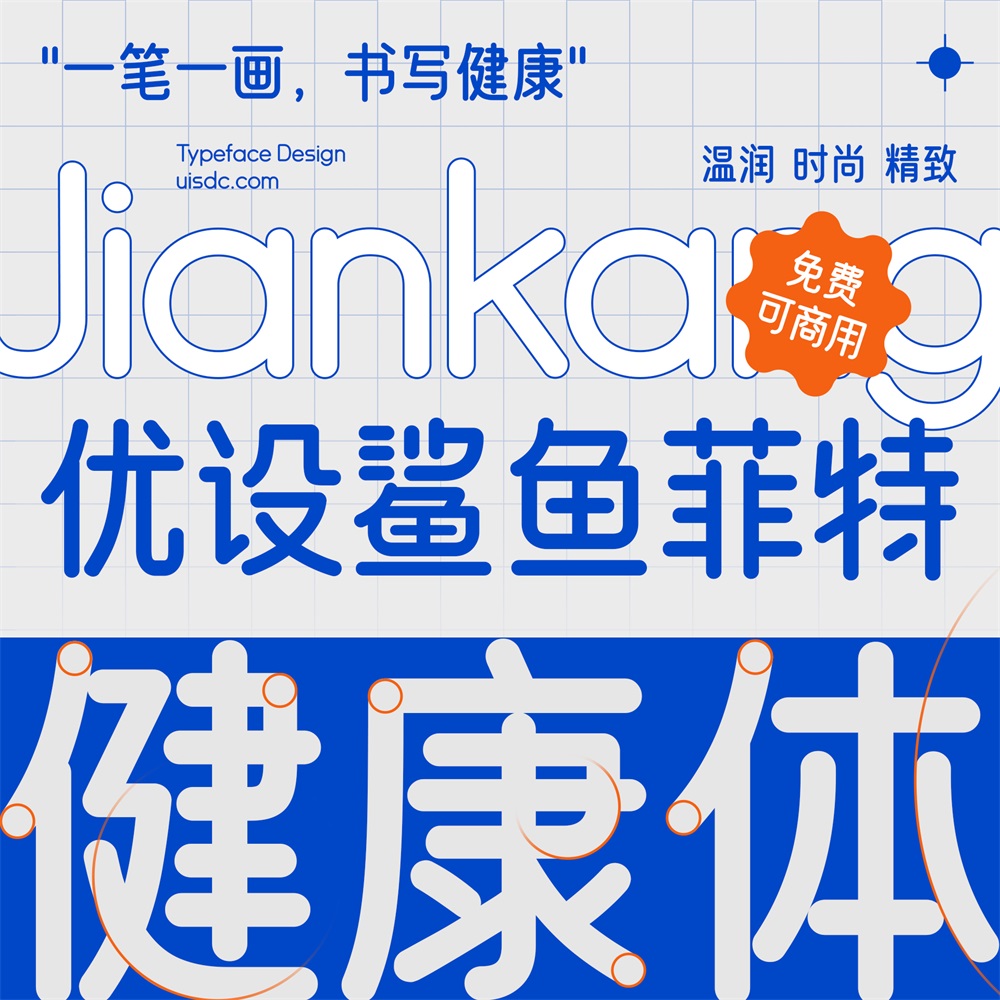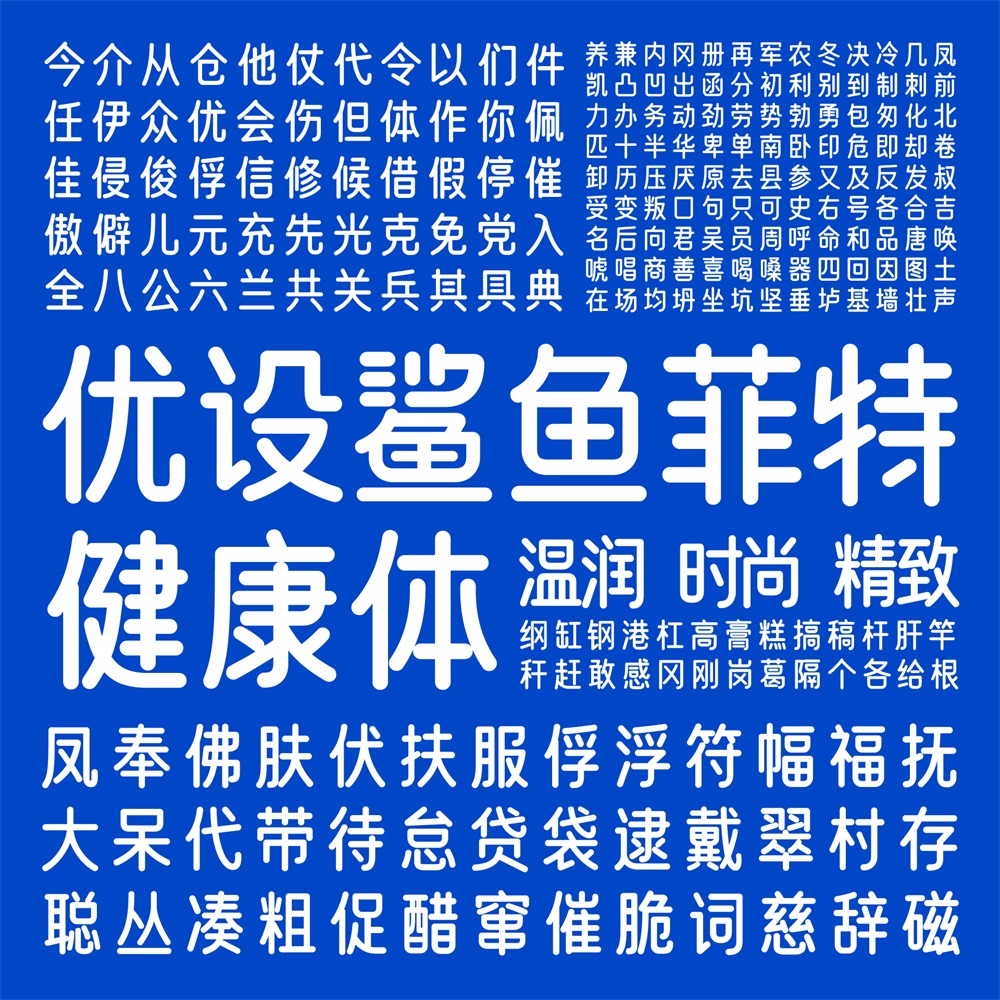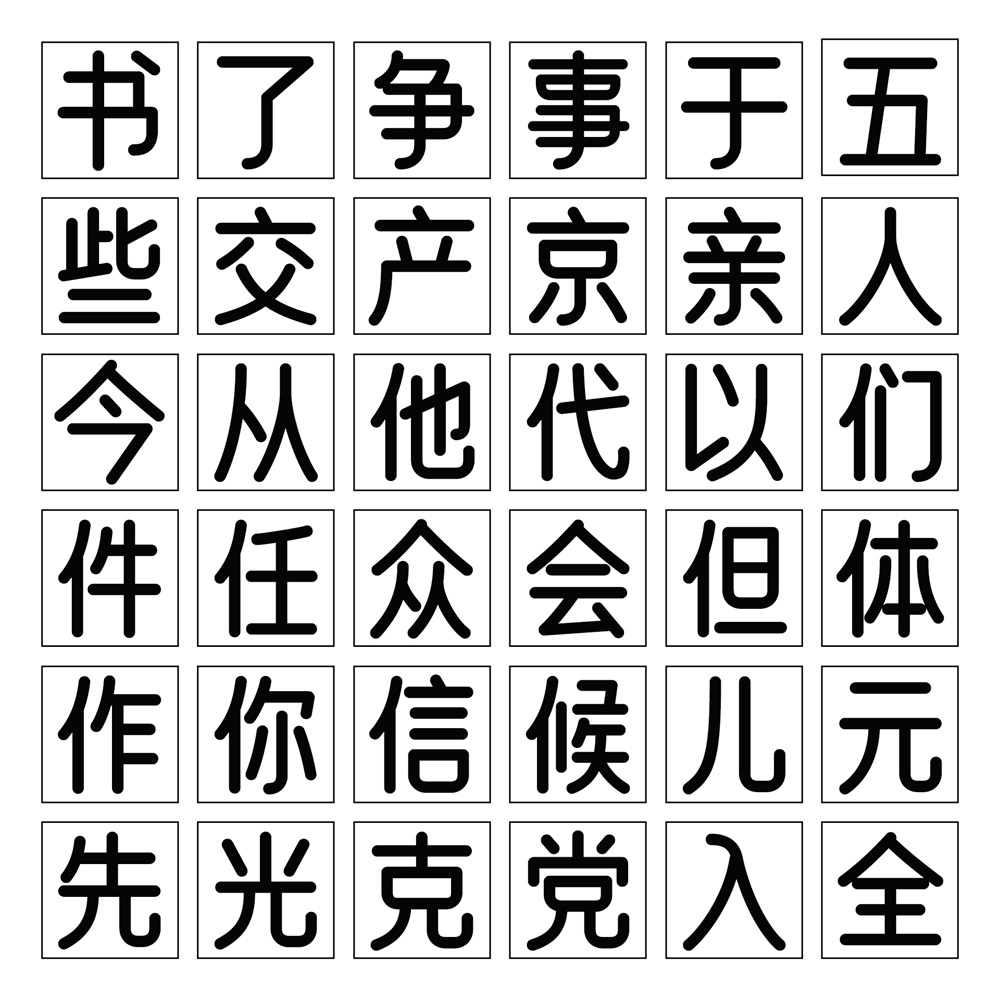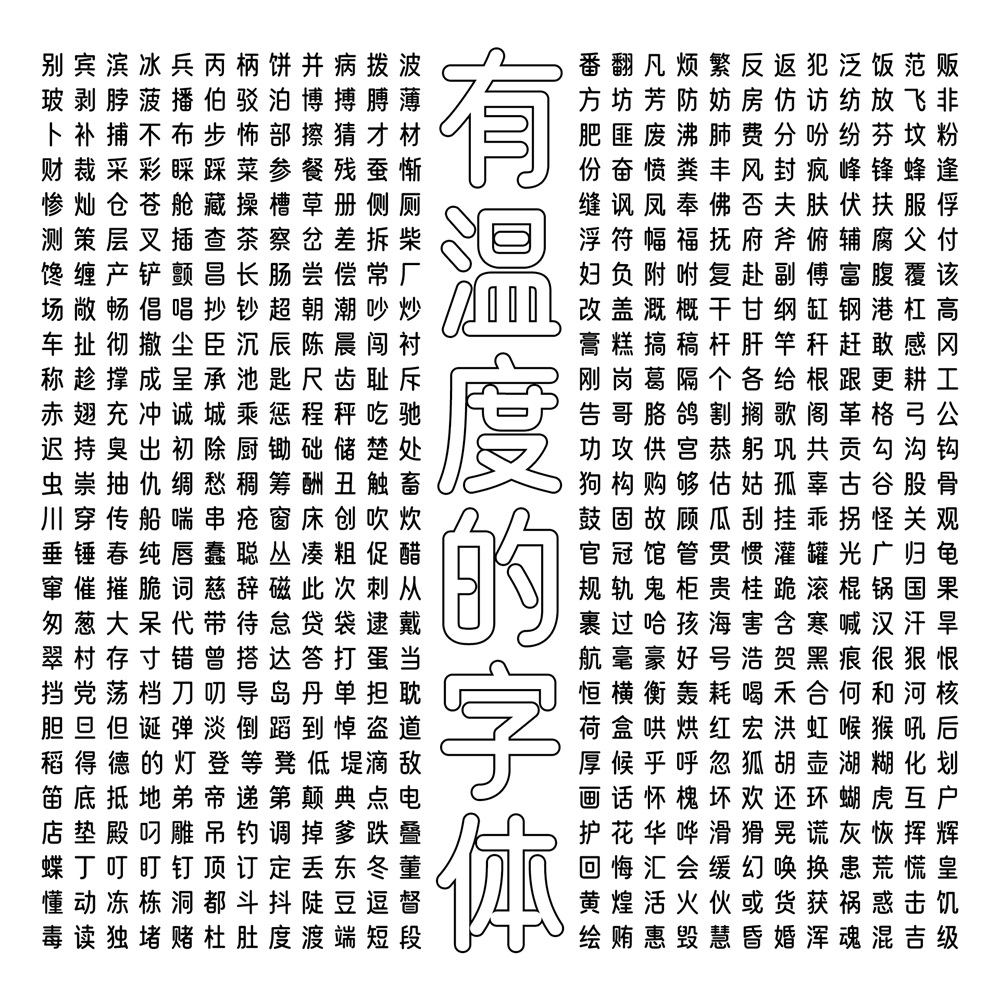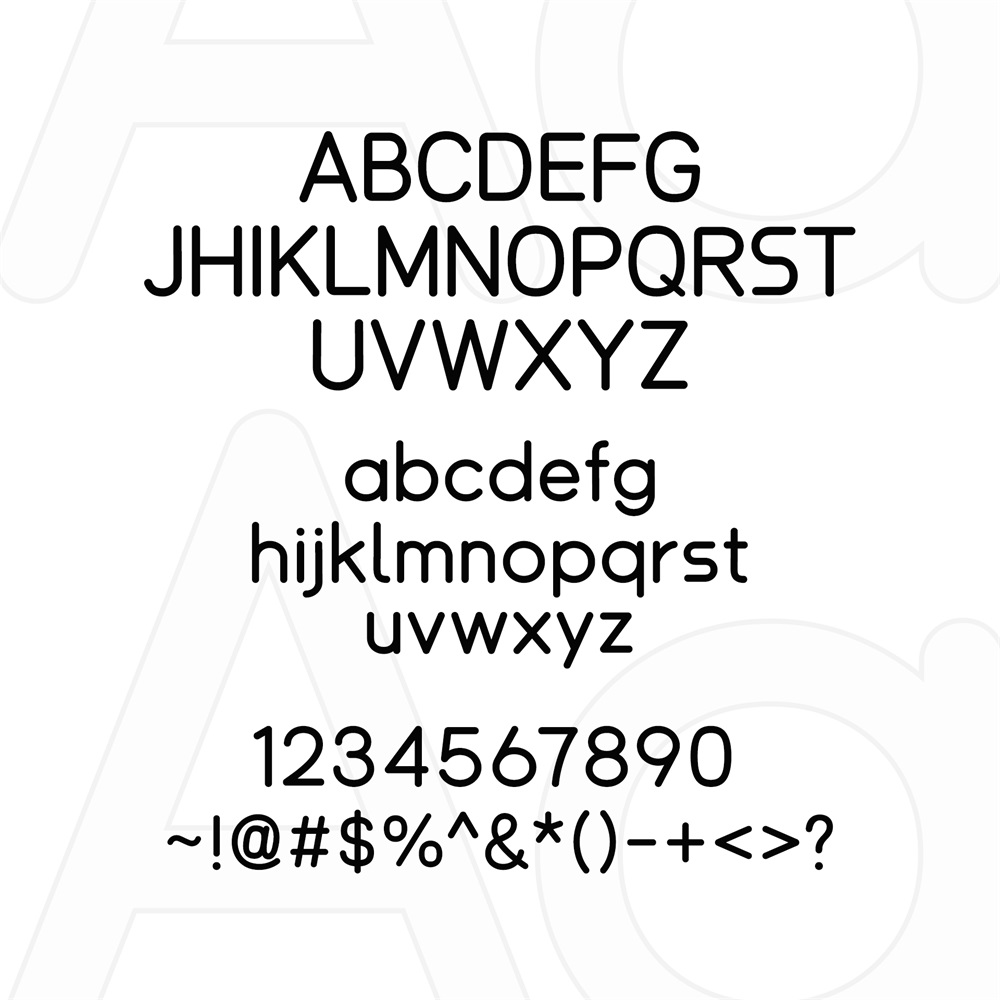
优设鲨鱼菲特健康体
字体简介
“优设鲨鱼菲特健康体”是一款由优设(UISDC)、字绘中国和字由联合新零售健康轻食品牌鲨鱼菲特开发的免费中文字体,于2022年11月20日发布。它属于无衬线圆体风格,基于“优设好身体”升级而来,字形纵向拉长,笔画圆润并带有硬挺细节,体现健康纤细与时尚稳重的特性。这款字体包含6763个汉字(符合GB2312标准),支持简体中文,适合电商设计、海报和品牌宣传等场景。